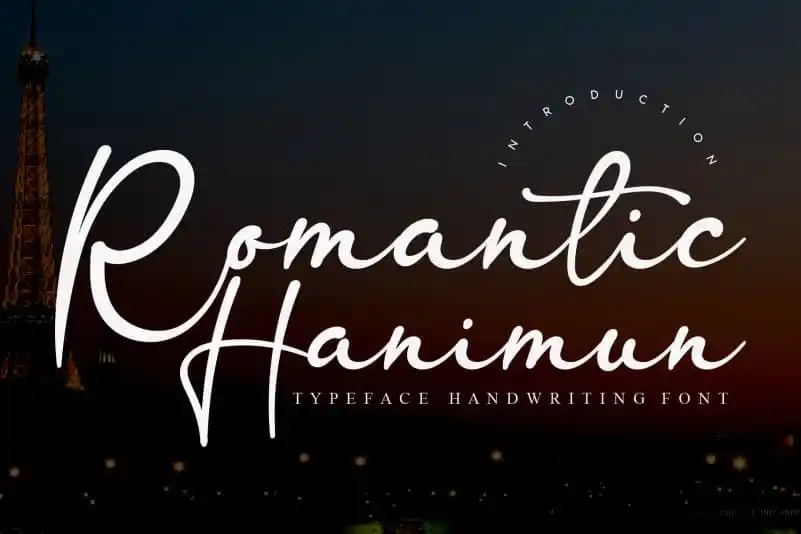
Romantic Hanimun Script Font – Download Grátis
Romantic Hanimun Script Font é a escolha perfeita para aqueles que valorizam um toque delicado e sofisticado em seus projetos digitais. Inspirada na natureza do próprio nome, esta fonte escrita à mão captura sentimentos românticos, ideais para aplicações como wall displays, cartões de casamento, logotipos nas mídias sociais, publicidade e embalagens de produtos. Com um toque delicado e elegante, essa fonte é perfeita para qualquer projeto que exija um sabor artesanal. Seja você um designer criando visualmente atraentes cartões de visita ou uma marca querendo personalizar suas propagandas, a Hanimun Script Font promete manter o seu projeto ao ar livre e na linha do tempo. Sua natureza delicada cria um contraste perfeito com outros elementos visuais mais formais, tornando-a ideal para trabalhos que buscam um toque de romantismo inconfundível.